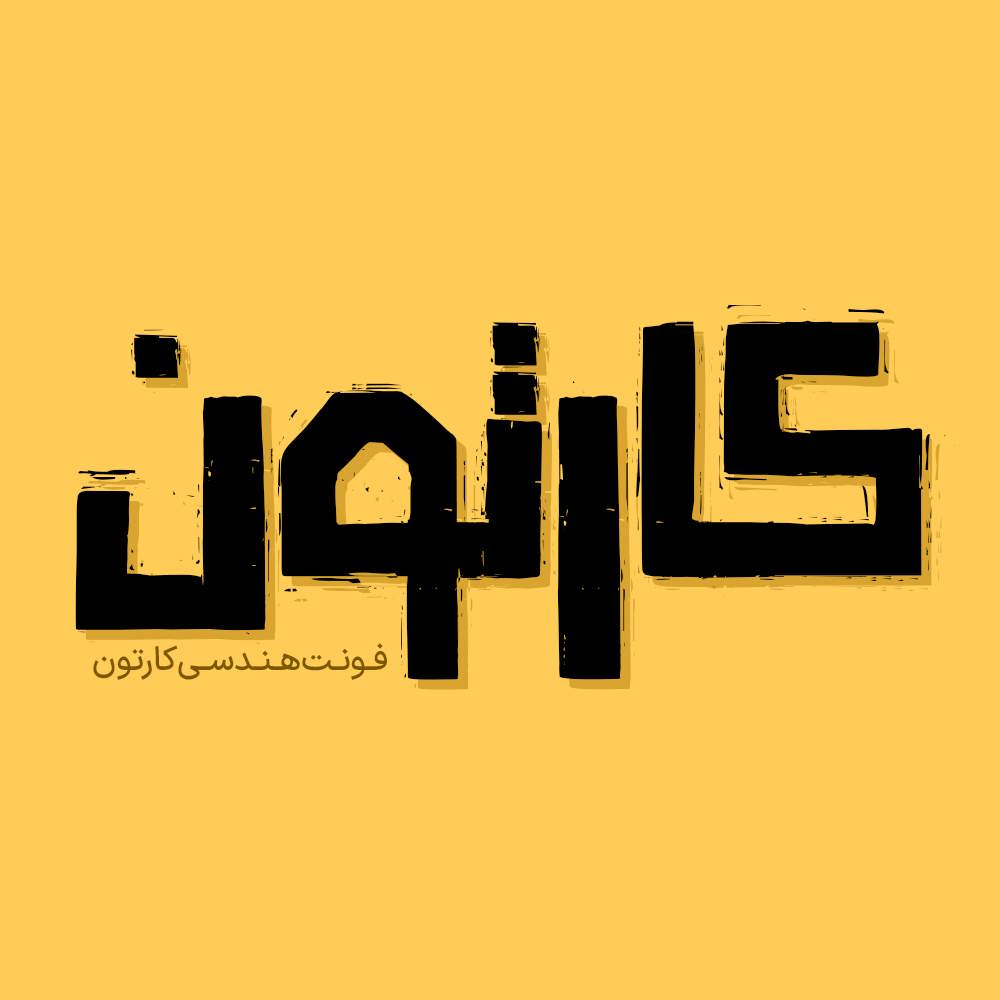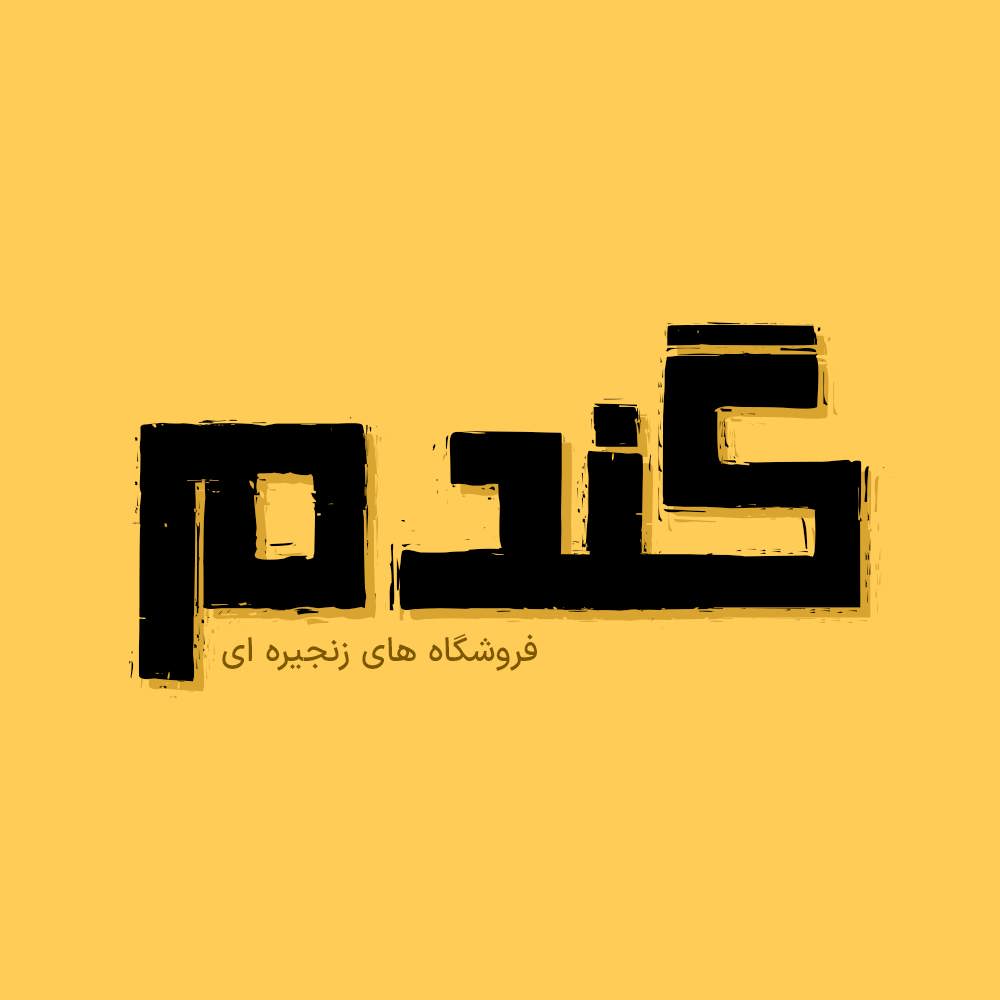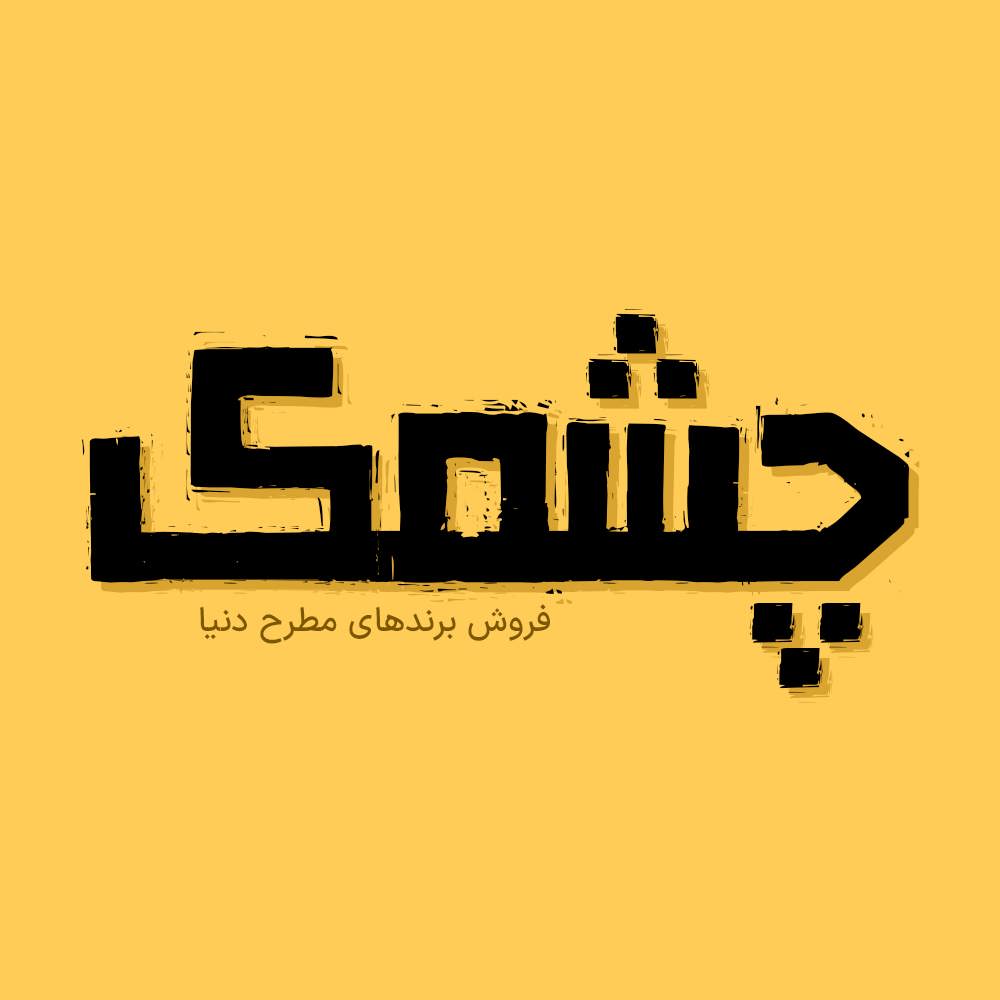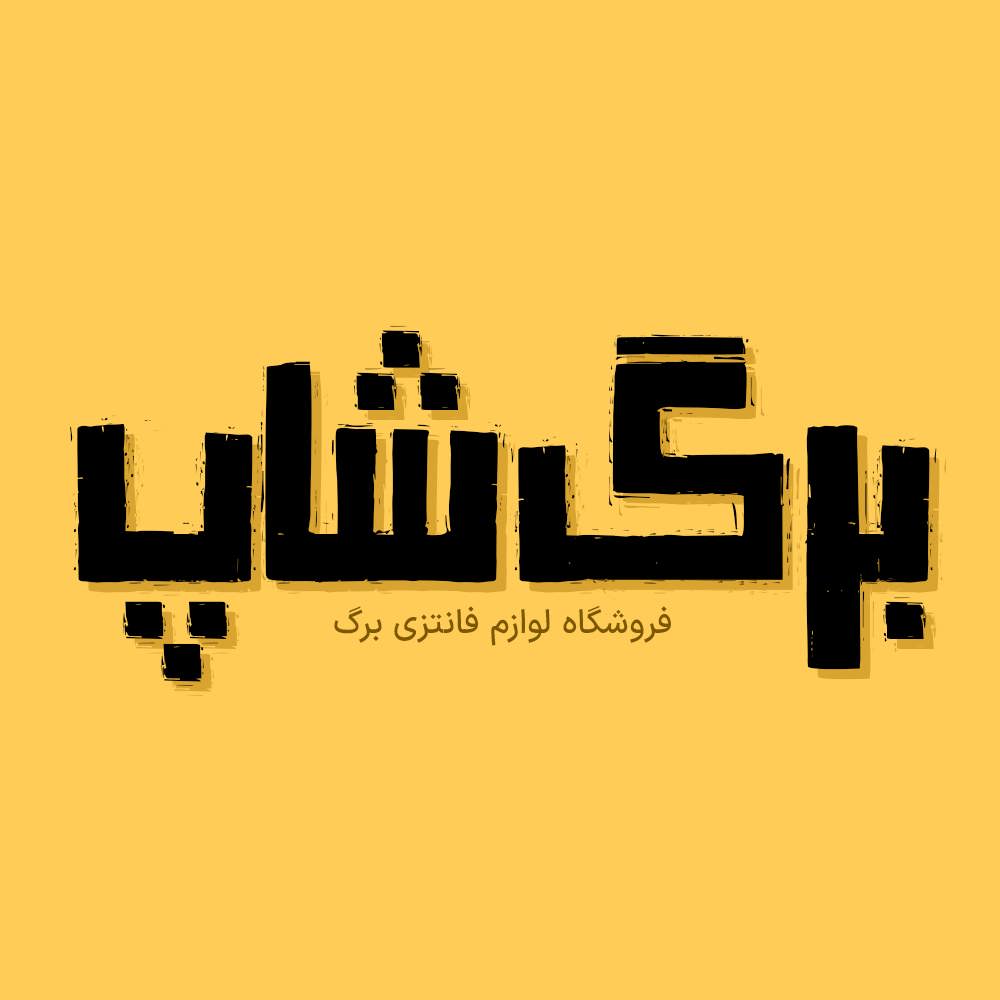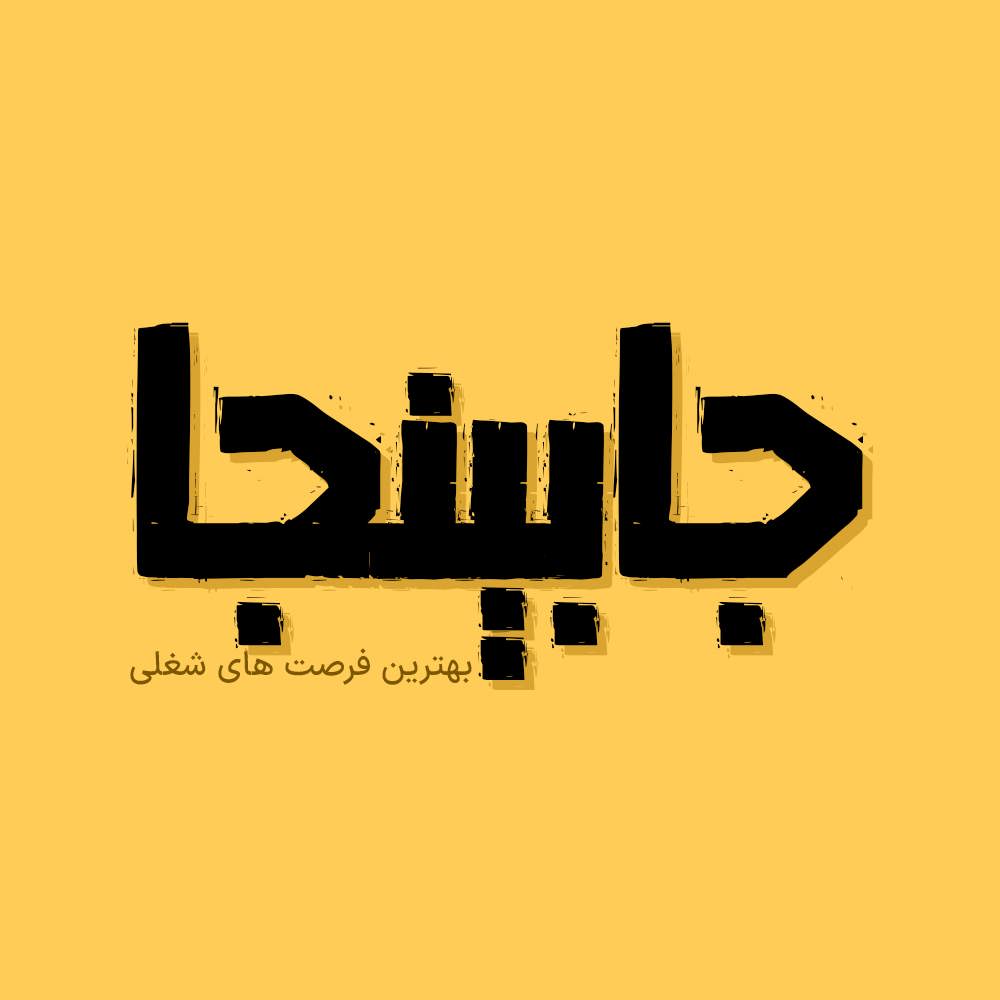
فونت فارسی کارتون Cartoon Font
فونت فارسی کارتون یک فونت تک وزن بولد و سنگین با کاربرد طراحی لوگوتایپ و طراحی های مختلف همچون کتاب و تولید محتوای متن های کوتاه…
فونت فارسی کارتون یک فونت تک وزن بولد و سنگین با کاربرد طراحی لوگوتایپ و طراحی های مختلف همچون کتاب و تولید محتوای متن های کوتاه و عناوین می باشد. این فونت با ساختار حروف خود مناسب استفاده در لوگوهای نوشتاری می باشد. همچنین از این فونت در طراحی تابلوهای چلنیوم هم به دلیل ساختار منحصر به فردش می توانید استفاده کنید. در ادامه برای شما نمونه تایپ های این محصول حرفه ای رو آماده کردیم که میتونید مشاهده کنید.